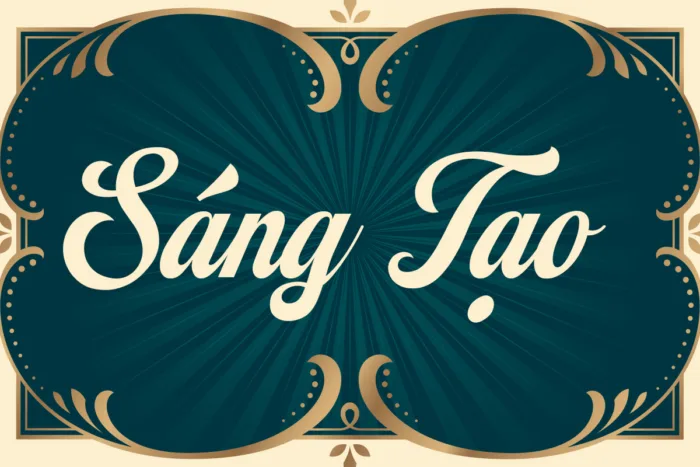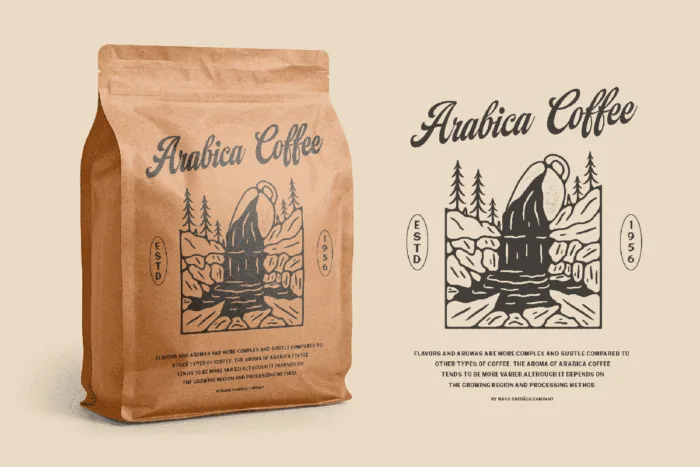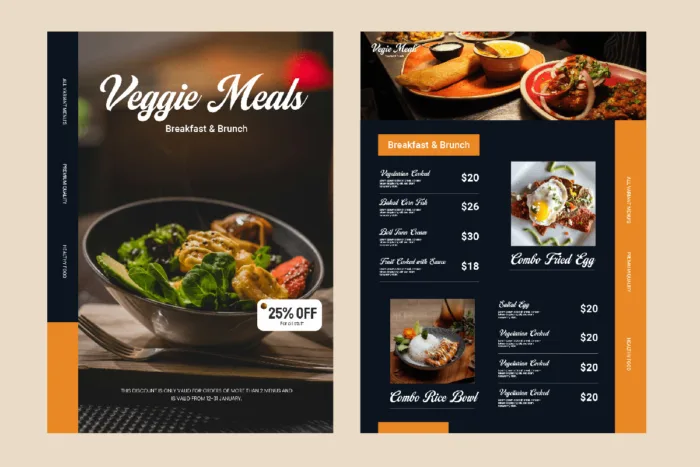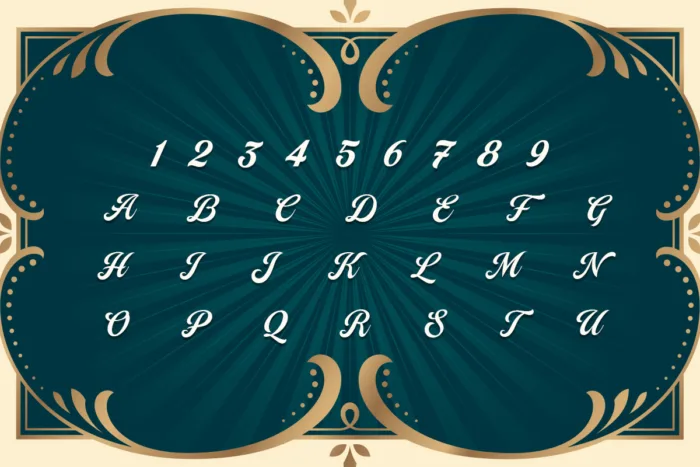
DVN Campana Script Việt hóa – Phiên bản đầy đủ bộ số, dấu
Campana Script là một font chữ script mang hơi hướng retro – lãng mạn, với những nét cong mềm mại và đường nối uyển chuyển. Phiên bản Việt hóa giữ nguyên tinh thần duyên dáng, đồng thời được tinh chỉnh bộ dấu tiếng Việt để đảm bảo tính thẩm mỹ và dễ đọc.
Font đặc biệt phù hợp cho:
-
Thiết kế bao bì cao cấp, mỹ phẩm, nước hoa.
-
Logo thương hiệu mang phong cách thanh lịch, cổ điển.
-
Poster, bìa sách, thiệp cưới và các ấn phẩm in ấn trang trí.
Với Campana Script Việt hóa, bạn sẽ dễ dàng tạo nên những thiết kế vừa sang trọng, vừa giàu cảm xúc, toát lên nét cổ điển nhưng không kém phần hiện đại.